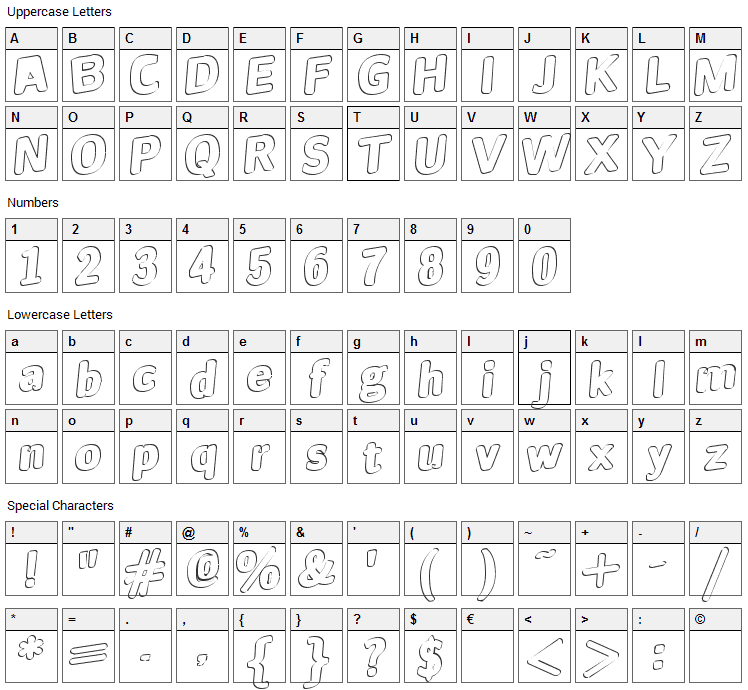
Arcane Names Font, Jinx Schrift, Digitale Download Schriftart
Schlagwörter:League of LegendsArcane Nine Schriftart
Arcane Nine Font
Jinx cosplay arcane kids
Arcane Nine Schriftart
Schriftart Arcane Nine
BN Jinx Schriftart
Set in the League of Legends universe, the series was produced by French animation studio .
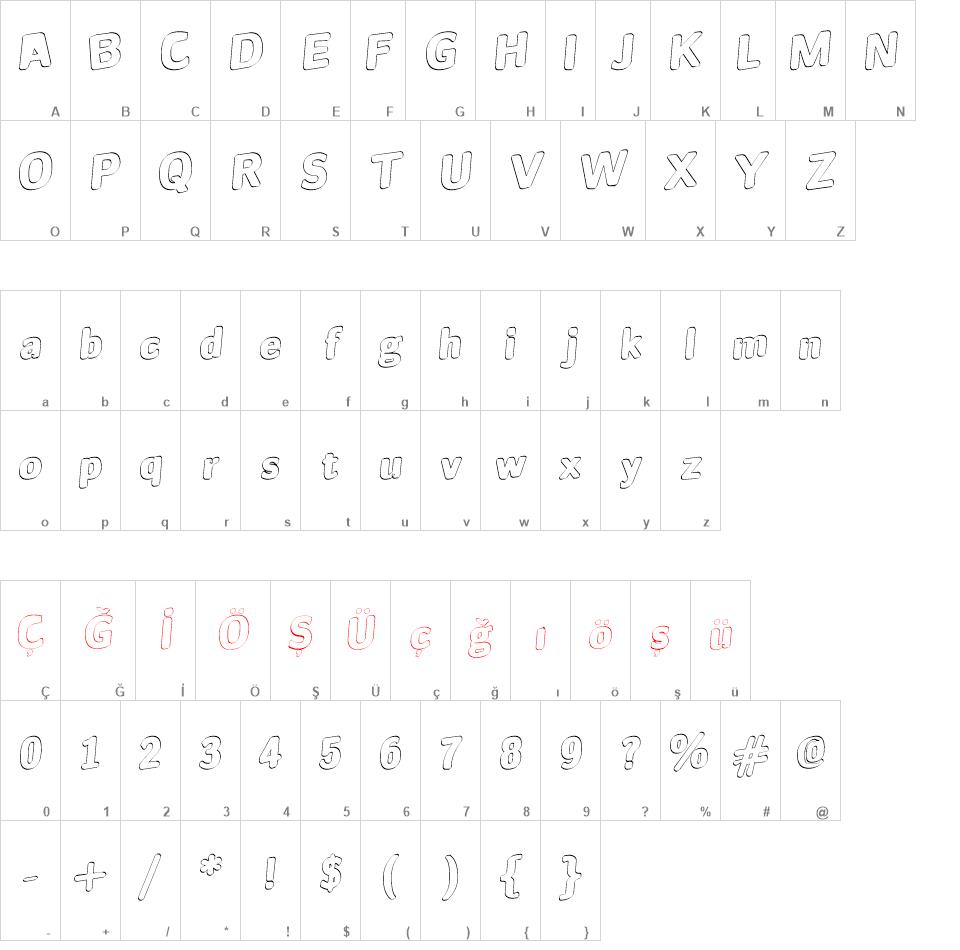
Arcane (TV series) Font
Generieren Sie einzigartige, stilvolle Texte mit unserem praktischen Font-Generator. Download Spende an den Autor .Inspired by Arcane League of Legends.
Arcane Font Generator
Schriftarten-Fonts.You can create a new font or edit the fonts included in this collection: Edit Collection.
Onkelz 2014 Schriftart
Using the above forms you can convert text into all sorts of different fonts including Old .Infos und Details über die Schriftart Jinx : inklusive TTF Vorschau Generator und Character Map (Buchstaben Mappe, Buchstaben Übersicht).Download free arcane nine font, view its character map and generate text-based images or logos with arcane nine font online.
Arcane namen schrift
Please donate if you like my work.
Schriftart BN Jinx
Arcane names font
View all glyphs (108) Luna.Die Rubrik „Text-Generatoren“ enthält einfache Tools, mit denen Sie Grafiken aus Schriftarten in verschiedenen Stilen und mit verschiedenen Texteffekten erstellen . Lassen Sie sich durch unsere Auswahl an kostenlosen und kommerziell nutzbaren Download-Fonts inspirieren. View all glyphs (219) Arcane .Schau dir unsere Auswahl an arcane namen schrift an, um die tollsten einzigartigen oder spezialgefertigten, handgemachten Stücke aus unseren Shops zu finden.There’s a great look-a-like font for it: https://fontlot.Font Meme is a fonts & typography resource. Der Jinx Font Download & weitere Fonts kostenlos auf MyFont.Schau dir unsere Auswahl an arcane names font an, um die tollsten einzigartigen oder spezialgefertigten, handgemachten Stücke aus unseren Shops zu finden.de – ber 130000 kostenlose Schriftarten und Fonts zum Download Hier gibt es Schriftarten und Fonts kostenlos, free und .Schau dir unsere Auswahl an jugendstil schrift an, um die tollsten einzigartigen oder spezialgefertigten, handgemachten Stücke aus unseren Shops zu finden.